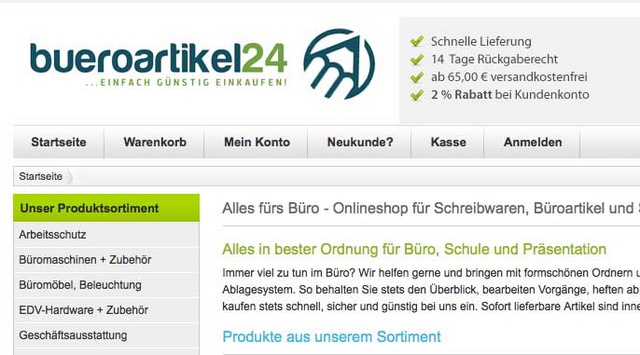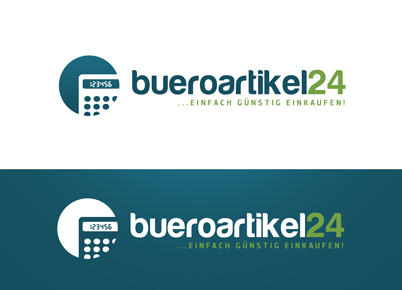
Welche Schriftart könnte das sein?
Hallo, bin auf der Suche nach der u.a. Schriftart. Habe schon alles mögliche ausprobiert. Aber leider weiß ich nicht mehr wie die Schriftart heißt. Vielleicht könnte einer der Typo-Experten mir weiter helfen.
Schriftart und Hersteller wären für mich interessant. Arbeite am Mac. Wir sind momentan auf der Suche nach einer neuen Schriftart
für unser Firmenlogo.
vielen Dank für deine schnelle Rückmeldung. Habe mir mal die Harabara
noch einmal angeschaut. Jetzt weiß ich genau was du meinst.
Das Verhältnis der Buchstaben zueinander stimmt nicht so recht.
Gibt es eine Schriftart die zu unserem Logo besser passen könnte?
Mir gefallen an der Harabara die ersten 6 Buchstaben unseres Firmennamens ganz gut.
Das Verhältnis der Buchstaben zueinander stimmt nicht so recht.
Wenn du den Schriftzug spationierst – in InDesign mit 25 – passt die Schrift hundertprozentig.
Wir sind momentan auf der Suche nach einer neuen Schriftart
für unser Firmenlogo.
Das ist doch das aktuelle, oder?
Ist doch gar nicht soooo schlecht.
Wenn es besser werden soll, beauftragt lieber einen Grafikdesigner oder eine Agentur, die Euch ein zusammenhängendes Corporate Design gestalten.
Ja das ist das aktuelle Logo. Leider gefällt uns die Schriftart nicht mehr so gut.
Wir haben uns eine Bildmarke erstellen lassen. Nur leider passte die alte Schriftart nicht mehr dazu.
Ist den die Harabara wirklich so schlecht?
Ich persönlich finde die Buchstaben "ueroar" ganz gut.
Die Spationierung der Schriftart Harabara ist standardmäßig nicht so schön.
Kennt Ihre vielleicht eine Schriftart die der Harabara ähnlich ist und vielleicht ein wenig hochwertiger ist?
Hätte da zwei Sachen zur Auswahl:
oder
Welches Logo gefällt euch besser?
Wenn du mit Spationierung die Zurichtung meinst, dann ist die bei so einem wenig umfangreichen Einsatz wie einem Namen unerheblich. Da kann man, oder muss man manchmal, eh nochmal per Hand bei gehen :-?
Ich musste zu erst an die Chalet von House Industries denken. Aber, ob das ein guter Ersatz ist, weiß ich nicht.
Die Bildmarken überzeugen mich beide nicht :neenee:
Zu dem Stift würde ich, wenn überhaupt eine wesentlich feinere Schrift wählen.
Aber was spricht denn dagegen, einfach nur den Schriftzug mit eindeutigen Farben* zu verwenden?
*Die Farben in den letzten Beispielen finde ich zu ›xingig‹ :-o
Die Schriftart Chalet NewYork 1970 gefällt mir sehr gut und ist der Harabara ähnlich.
"Die Bildmarken überzeugen mich beide nicht "
Schade, hätte wirklich gedacht das die Bildmarke besser ankommt. Soll ich die Bildmarke kleiner bzw. dünner machen? Oder ist es die Bildmarke bzw. das Bild selbst was dich nicht anspricht? Oder ist ein "Buntstift" die falsche Wahlfür ein Logo?
"Aber was spricht denn dagegen, einfach nur den Schriftzug mit eindeutigen Farben* zu verwenden?"
Das noch aktuelle Logo besteht nur einem Schriftzug in 2 Farben. Leider ist das Logo bzw. der Schriftzug recht breit und die Farben gefallen auch nicht jedem.
Welches Logo sagt dir persönlich mehr zu ? Das alte oder das "neue" mit der Harabara Schriftart?
So richtig habe ich aber noch keine Schriftart gefunden. Es sollte eine Schriftart sein die Einprägsam ist und bei der die "24" sehr schön zur gestung kommt. Zusätzlich sollte sie ein wenig abgerundet sein.